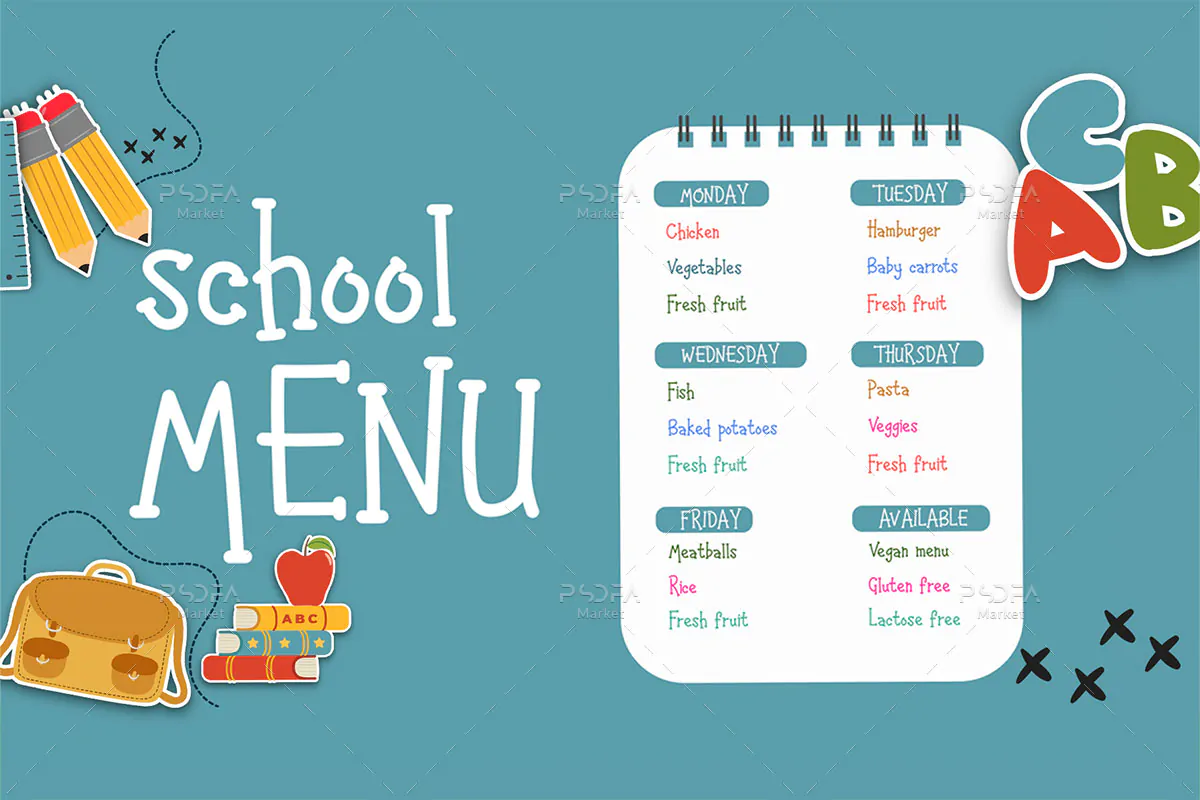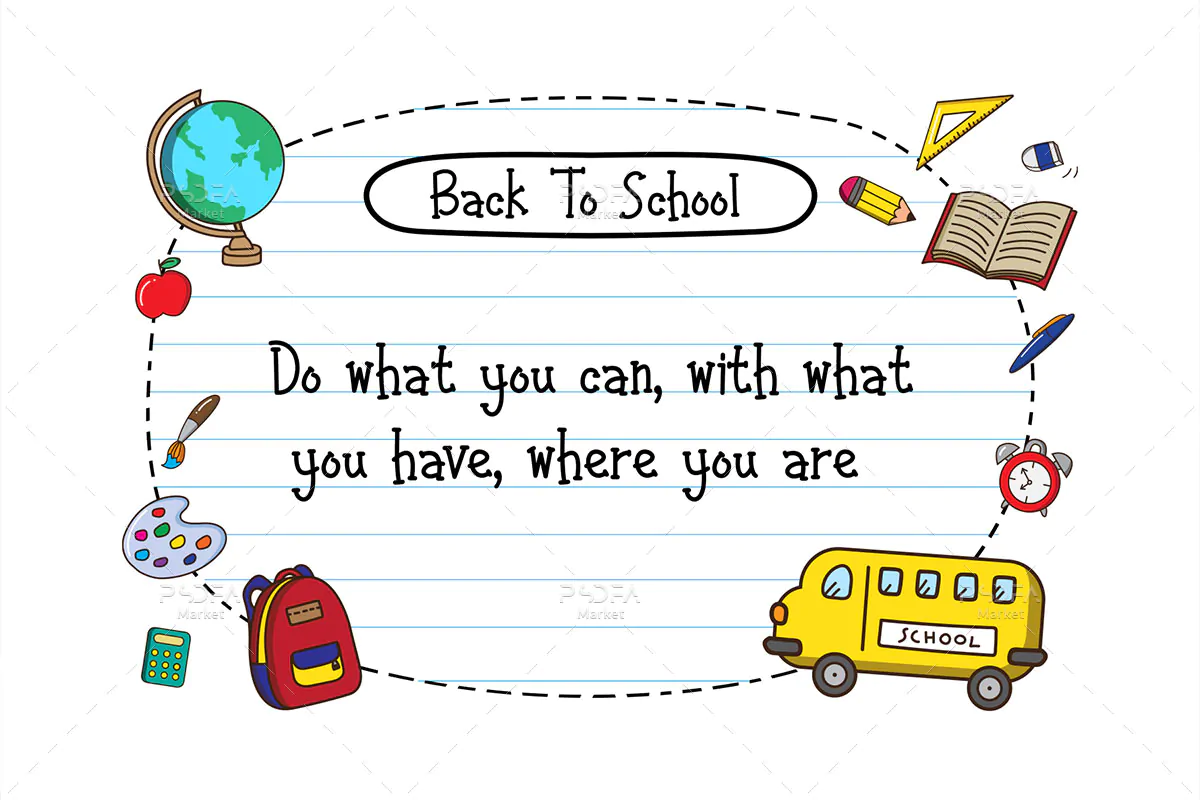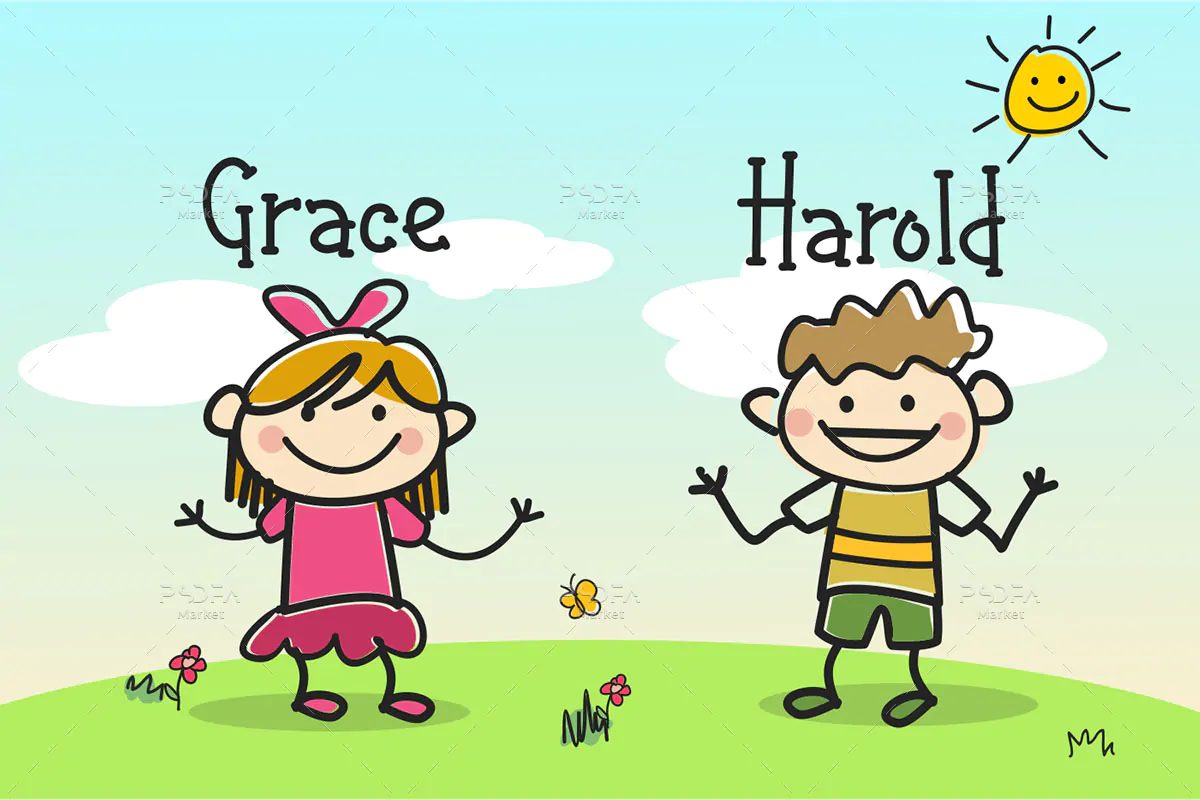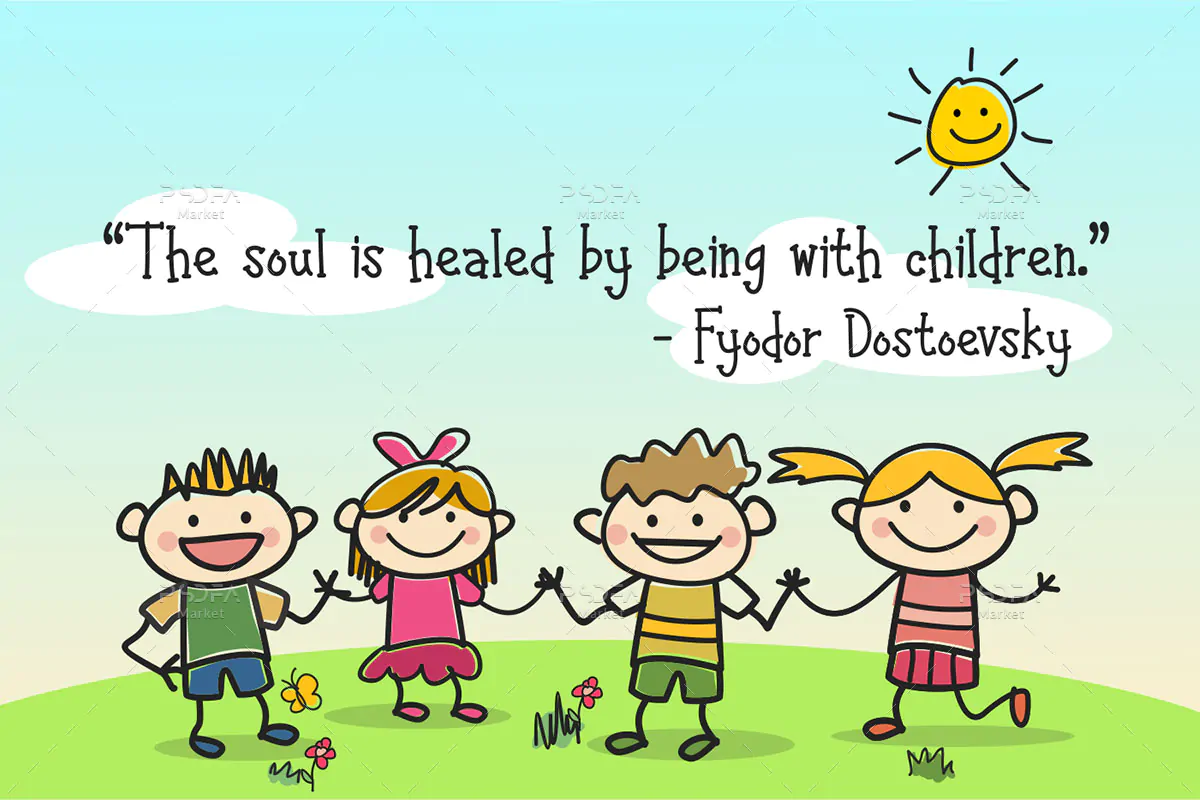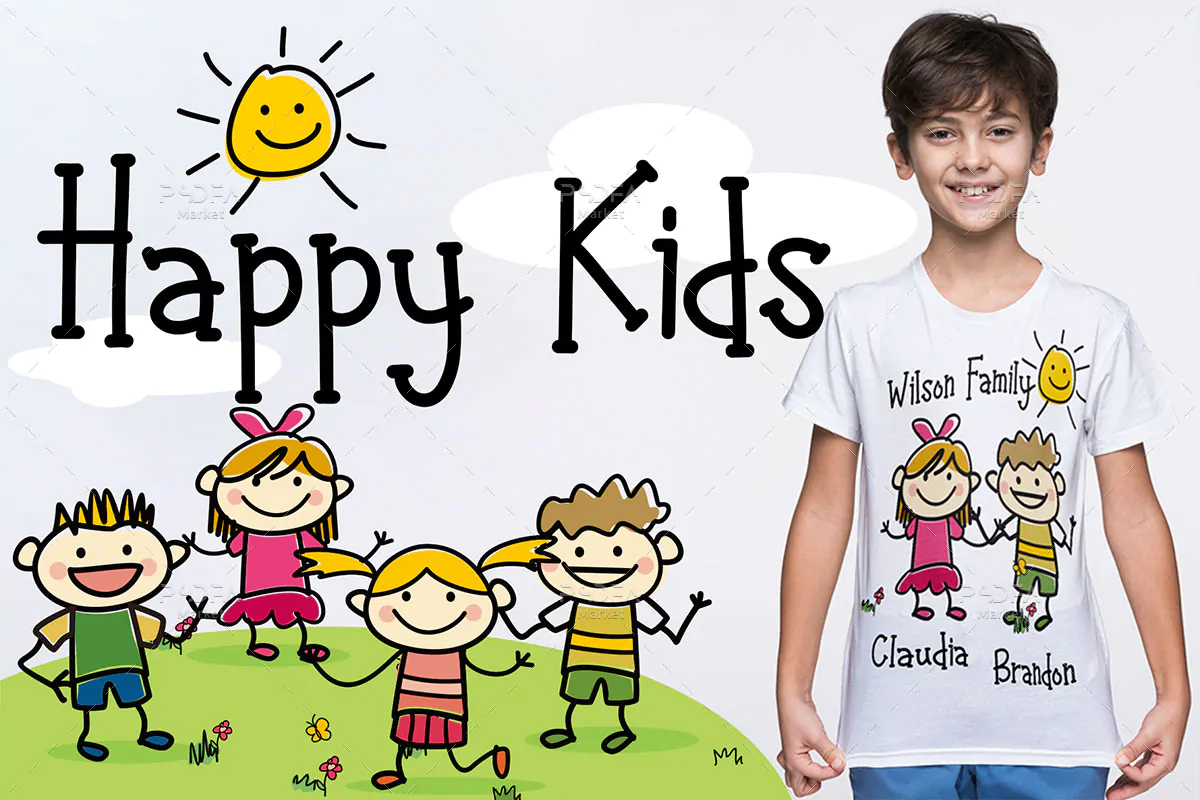
فونت کودکانه انگلیسی Happy Kids
فونت کودکانه انگلیسی Happy Kids یک قلم نمایشی شاد و فانتزی است که مناسب جهت استفاده در طرحهای کارتونی و کودکانه میباشد. فونت Happy Kids با وزن معمولی طراحی شده است که میتوانید از آن در طراحی کارت تبریک، پوستر، بسته بندی محصولات، تقویم، لوازم التحریر، ظروف یکبار مصرف، استیکر و … استفاده کنید.